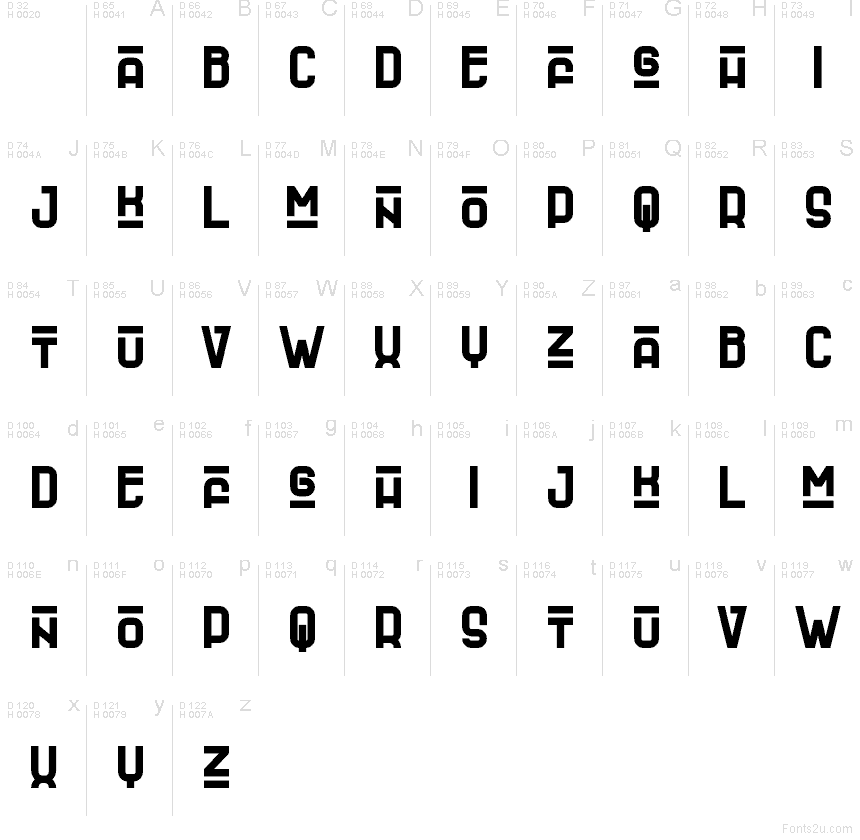
Foreigner Book od Vladimira Nikolice je bezplatné geometrické bezpatkové písmo typu display, vytvořené z širokých tahů a ostře čtvercových tvarů. Jeho stlačené spoje, zaoblené obdélníkové otvory a prudké změny šířky písmen vytvářejí hutnou, technickou siluetu s výrazně futuristickým nádechem.
Nejzdařileji se uplatňuje v identitě elektronické hudby, protože jeho bloková konstrukce připomíná nápisy vyřezané do ovládacích panelů a krytů strojů. Může také dodávat podobu sci-fi plakátům, herní grafice a technologickým obalům, kde jeho dříky a uzavřené prostory mohou připomínat obvodové spoje, průmyslová schémata a ostré hrany ilustrovaného hardwaru, namísto toho, aby sloužilo jako neutrální text.